A, O y S construidas en Cinema 4D como volúmenes de arcilla con agujas metálicas insertadas. La textura de huella dactilar y su distribución sobre la superficie son procedurales — los objetos no existen físicamente. El ejercicio explora qué ocurre cuando se traslada la lógica artesanal del taller a un entorno de simulación digital.
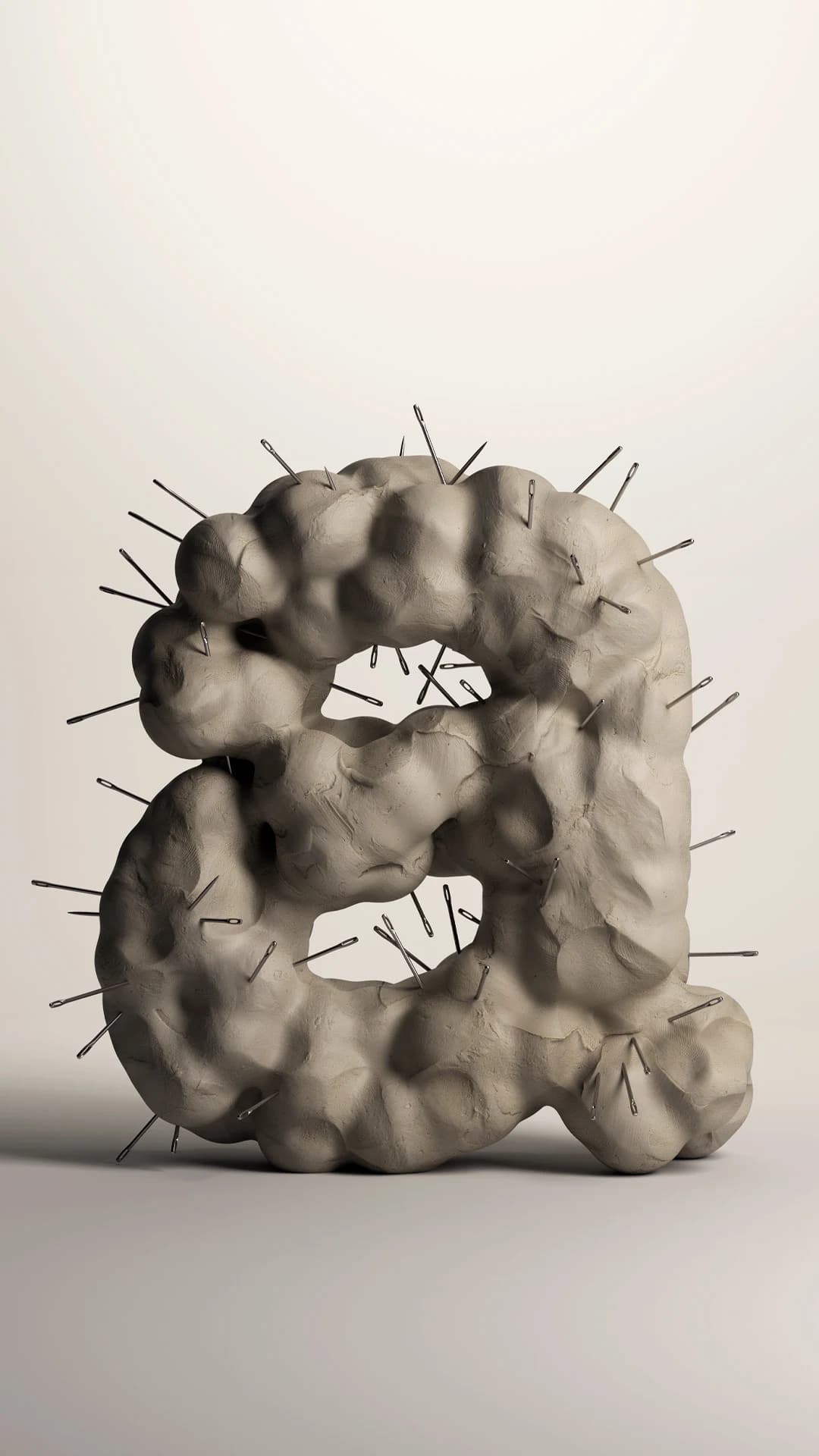
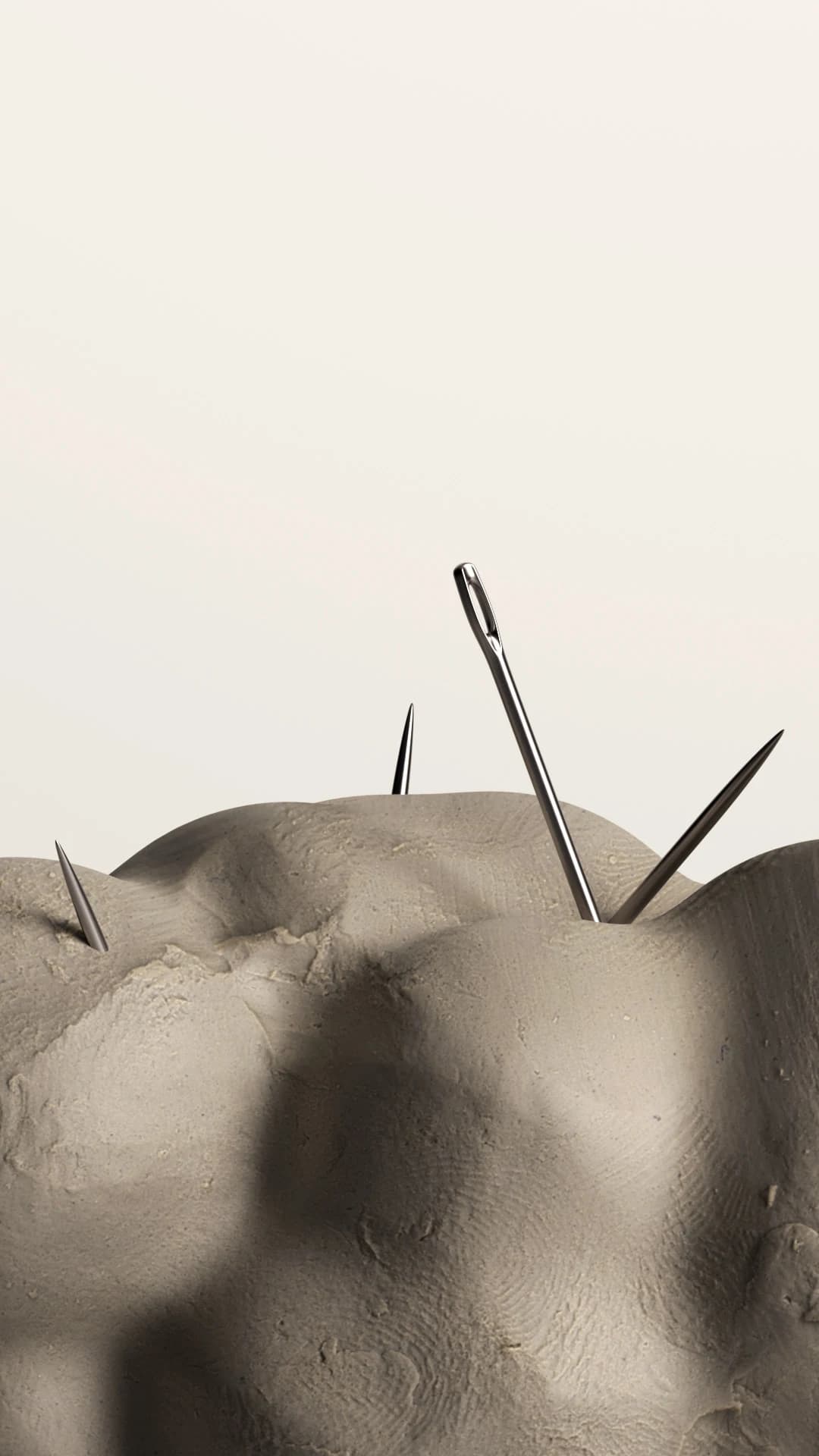
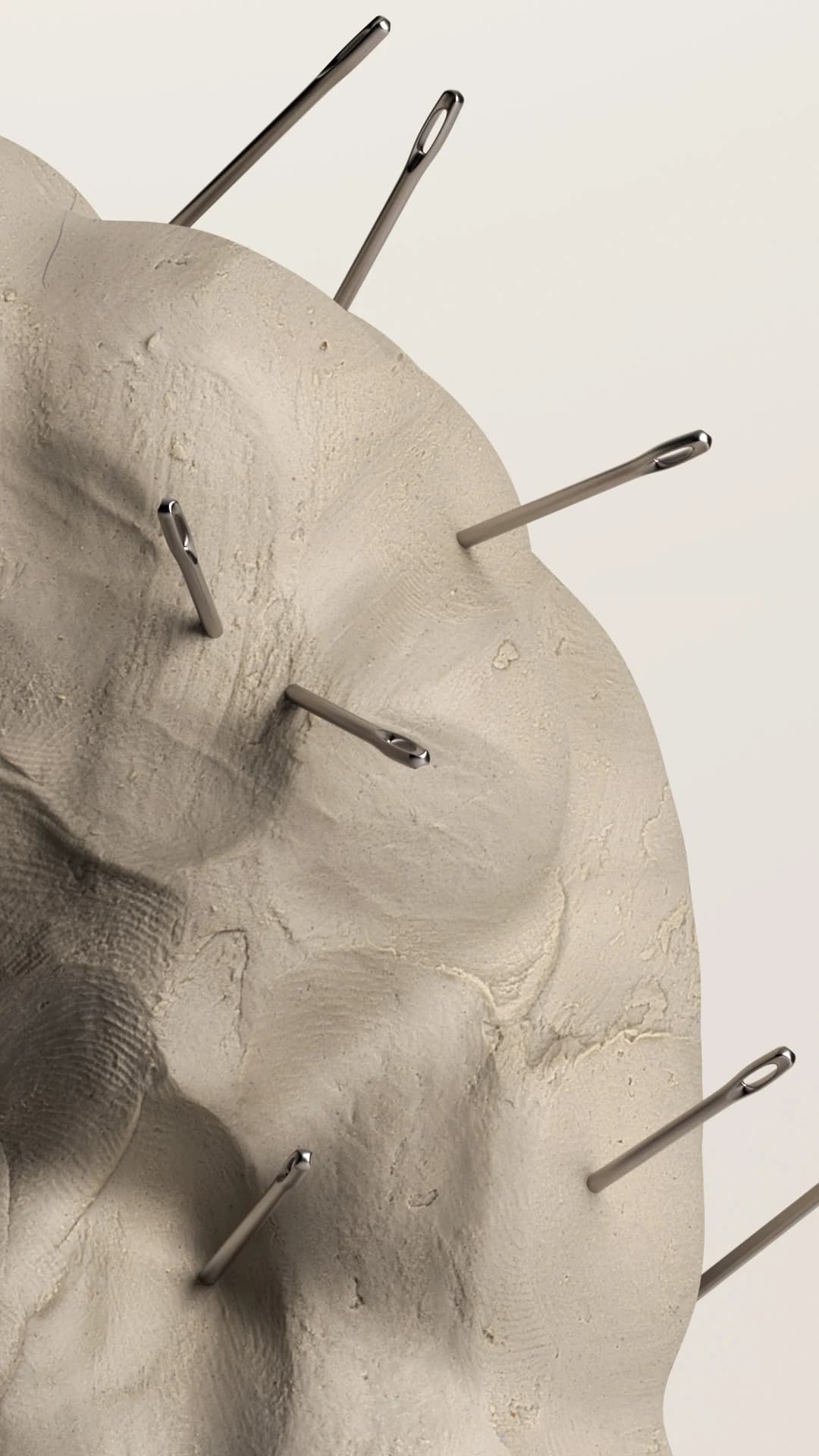
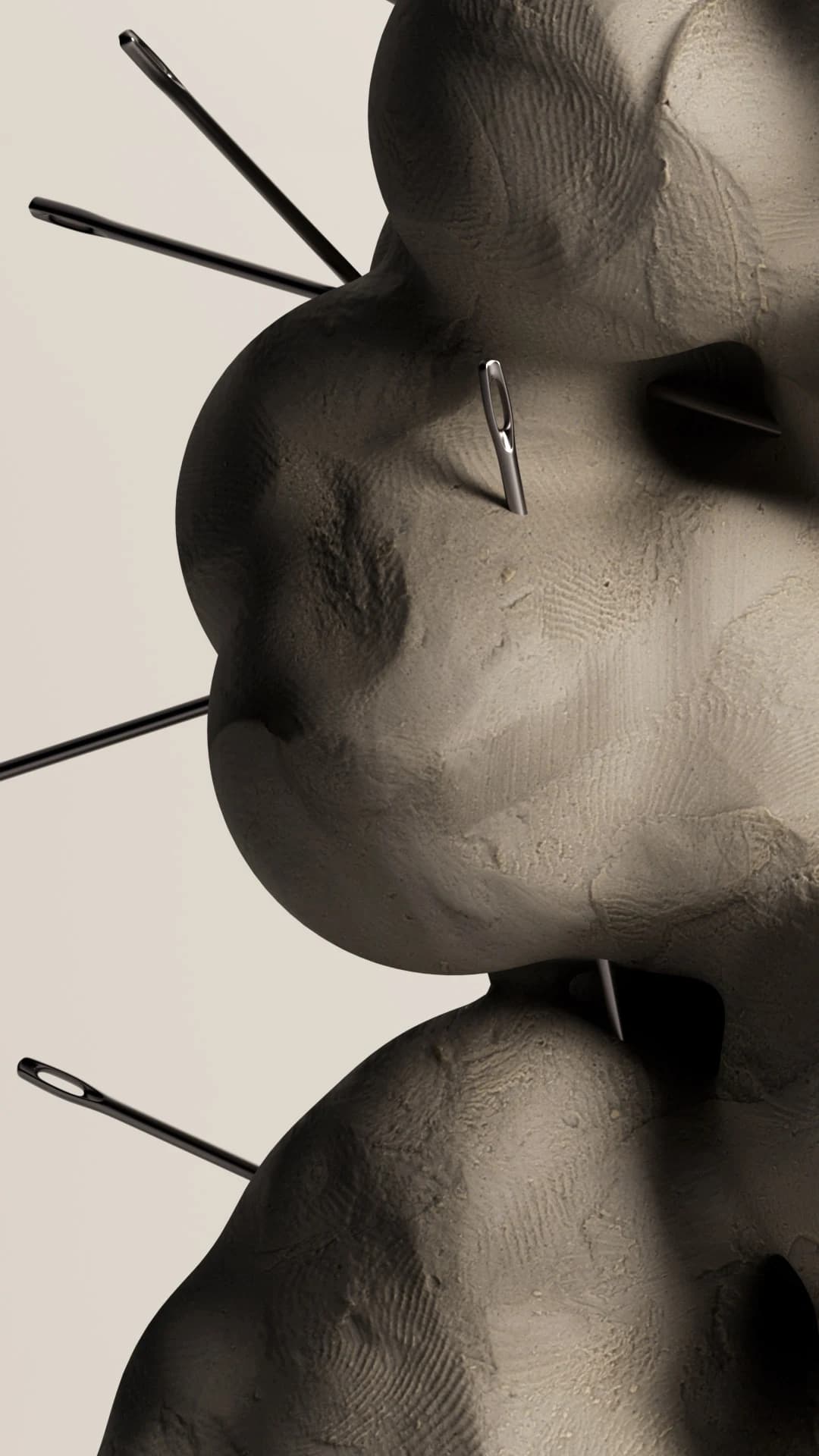
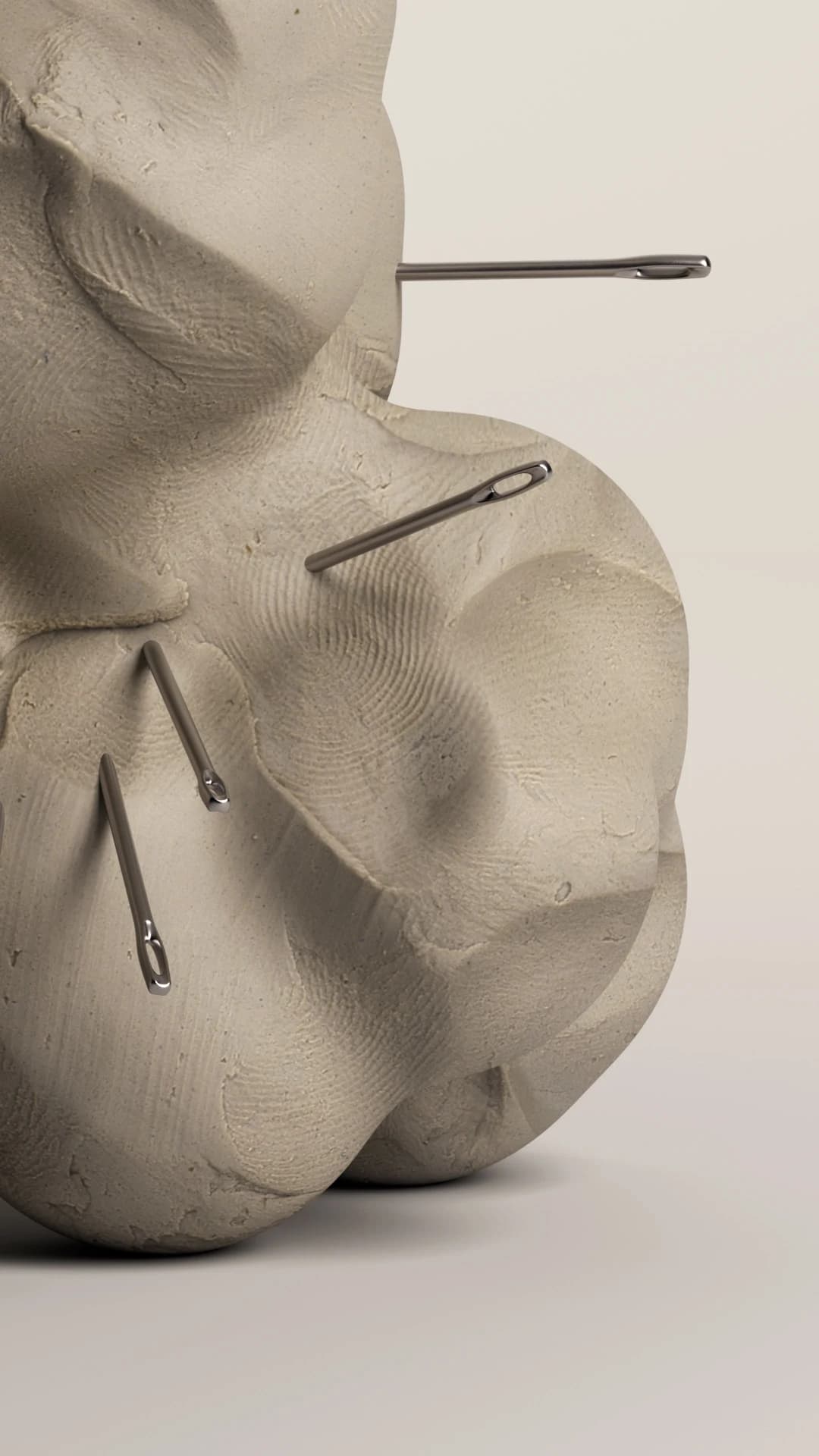
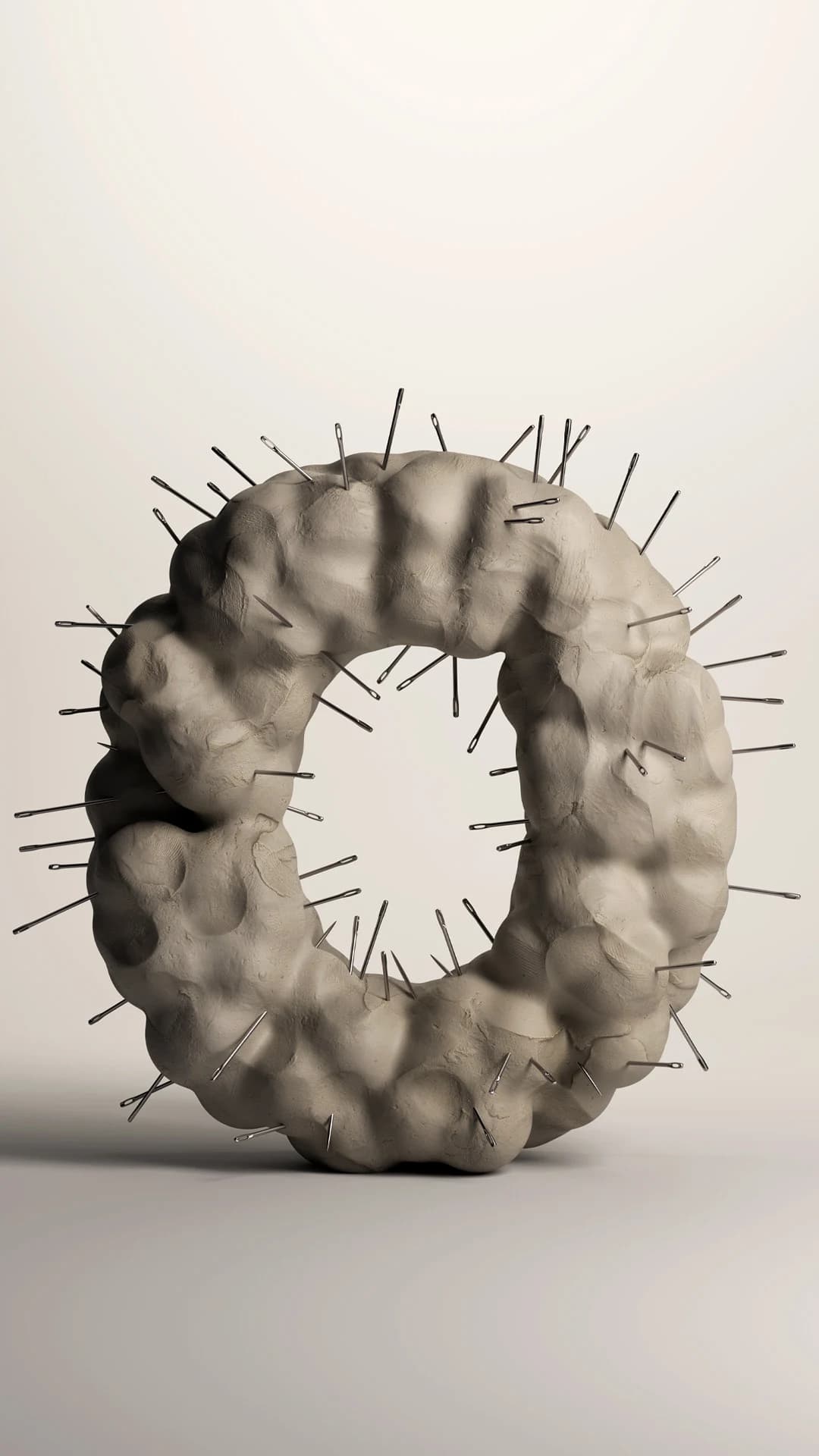
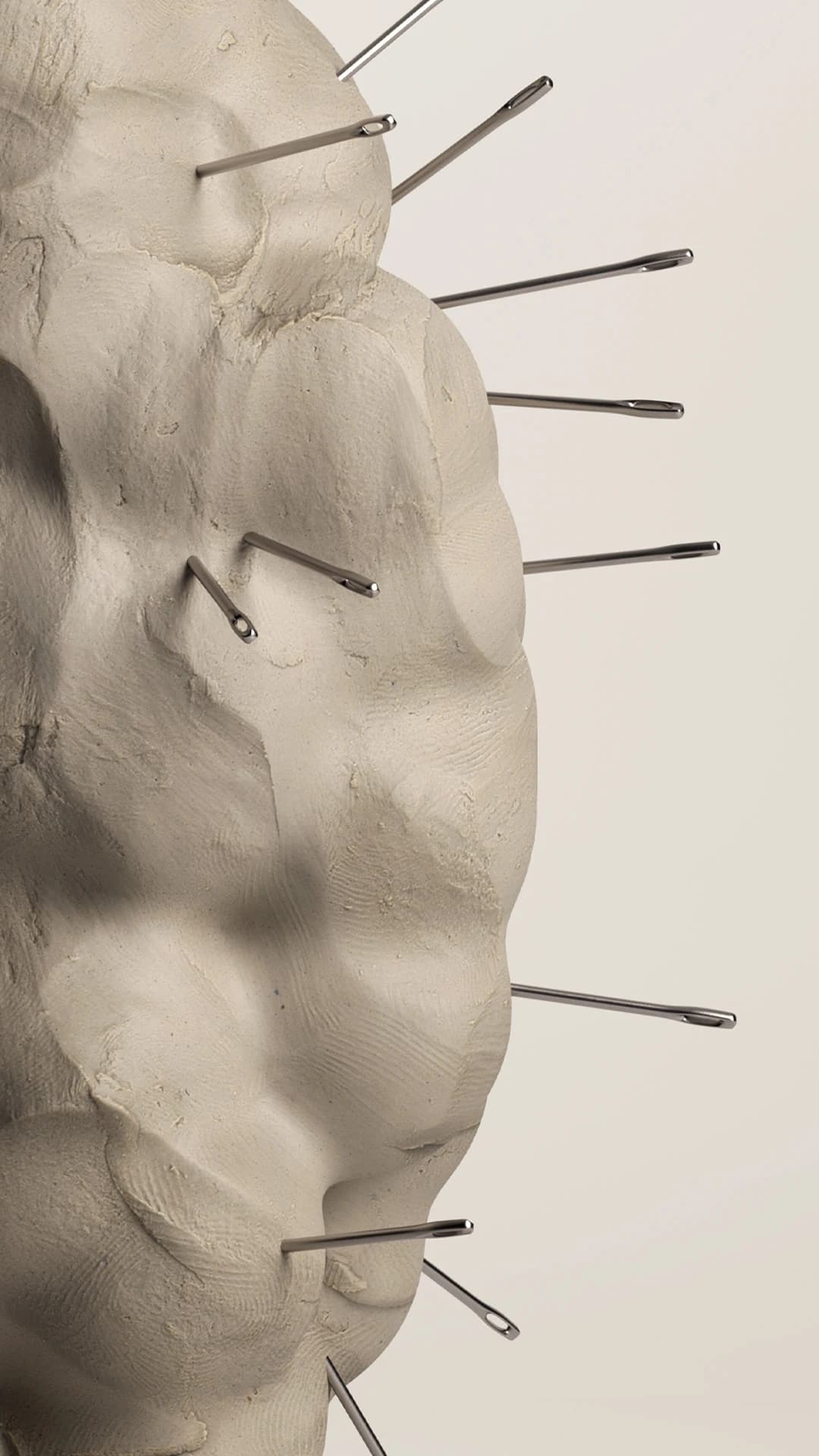
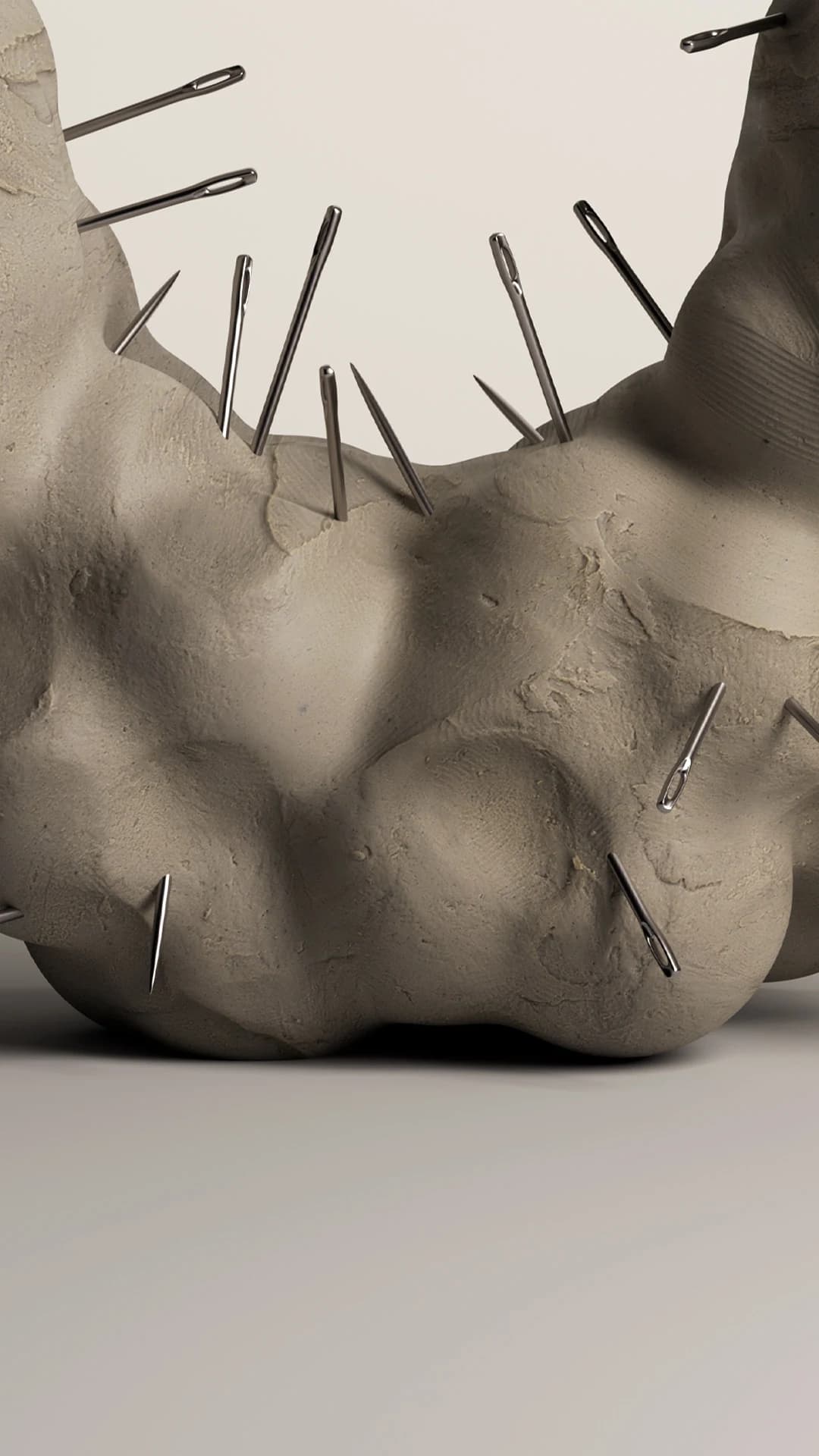
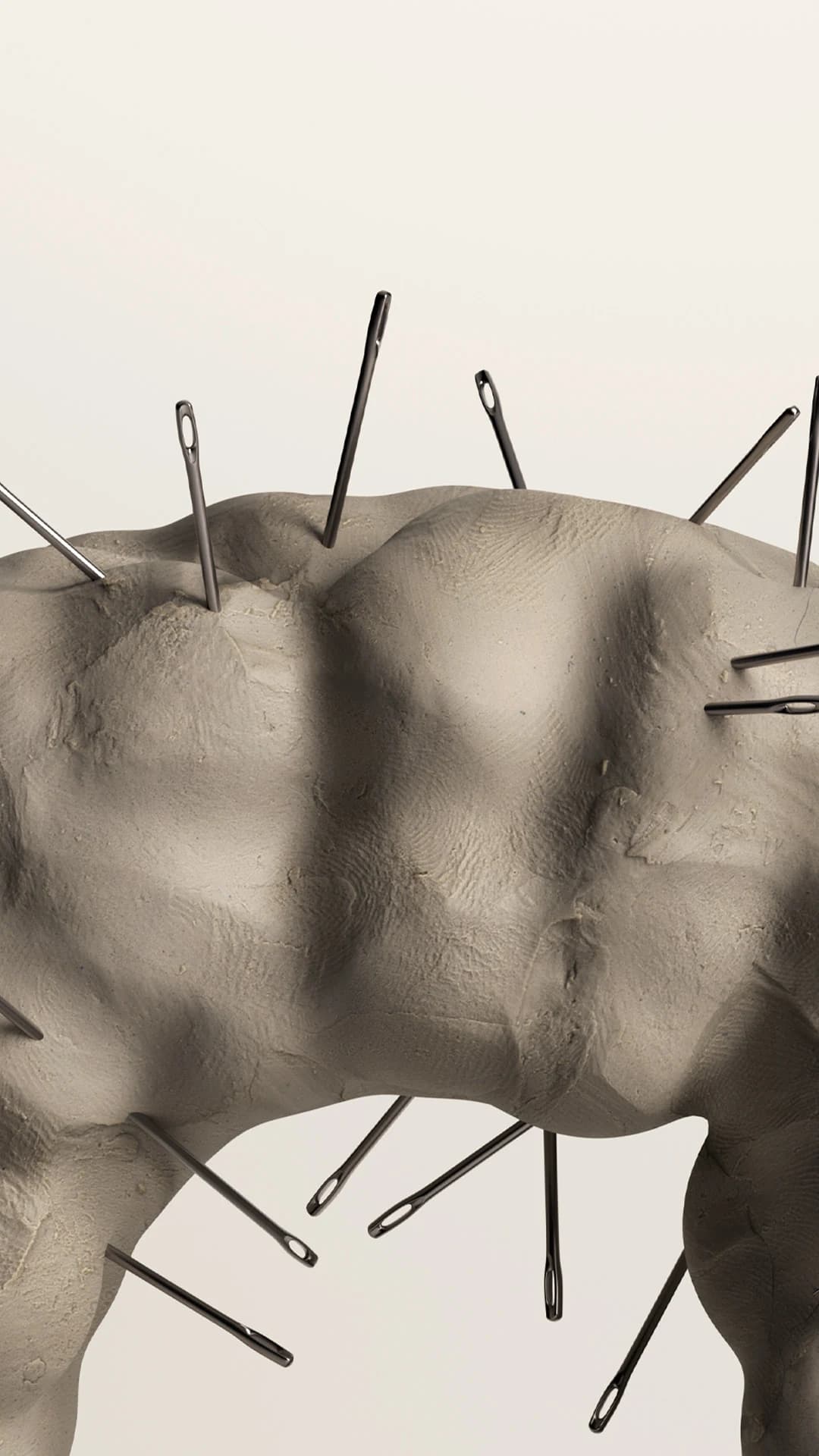
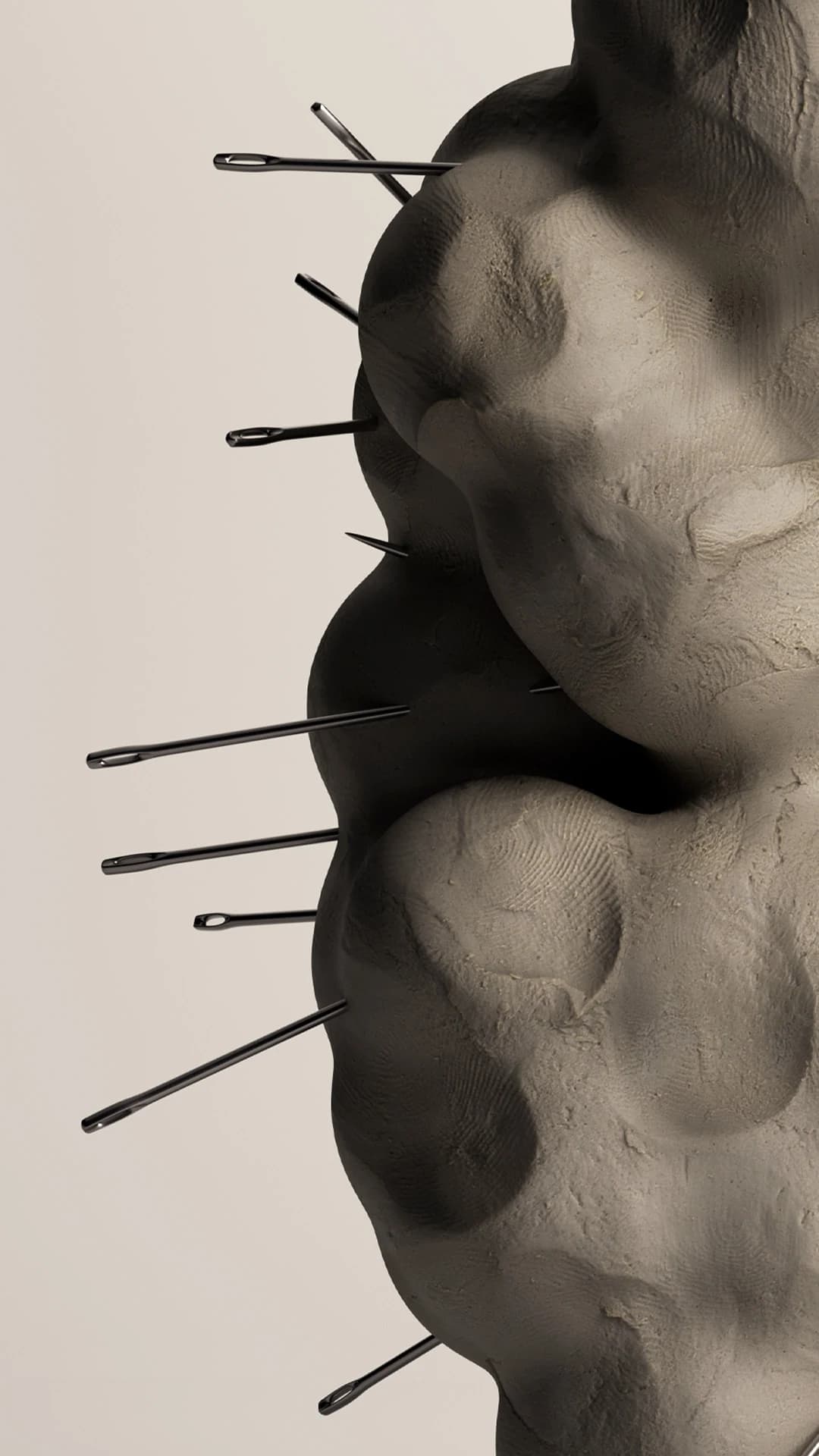
El modelado de punzones en acero, la talla de tipos en madera o el trabajo en plastilina como paso previo al fundido producen marcas propias del proceso físico — irregularidades, huellas, presión visible. Esas marcas son consecuencias del material, no decisiones estéticas. Este ejercicio simula esas propiedades en un entorno digital: la densidad de agujas, la distribución de la textura y la orientación de la luz son parámetros ajustables, no consecuencias del barro.
Tres caracteres (A, O, S) construidos desde acumulación de esferas de radio variable. Las agujas se posicionan siguiendo vectores definidos por la geometría de cada letra. La textura de huella dactilar se genera mediante ruido procedural de alta frecuencia aplicado al displacement del material.
Modelado de letras por acumulación esférica → definición del sistema de agujas por geometría de carácter → generación de textura procedural (huella dactilar) → iluminación lateral difusa → selección de encuadres por carácter.